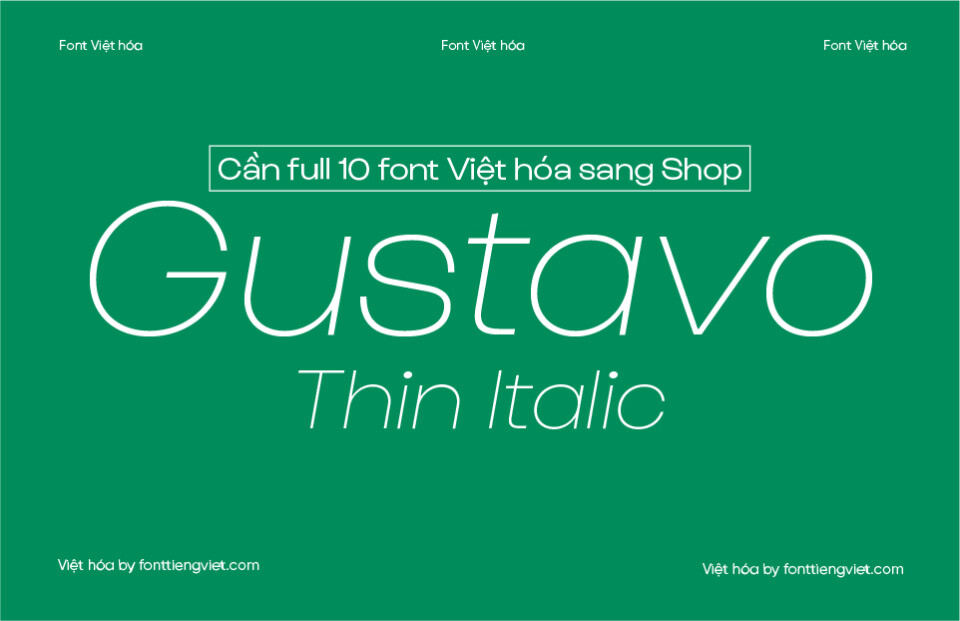
Font Việt hóa 1FTV VIP Gustavo Thin Italic
Giới thiệu về Font Việt hóa 1FTV VIP Gustavo Thin Italic
Trong thế giới đồ họa hiện đại, việc lựa chọn một bộ Font Miễn Phí chất lượng luôn là ưu tiên hàng đầu của các nhà thiết kế. Đặc biệt, mẫu Font Việt hóa 1FTV VIP Gustavo Thin Italic đang trở thành một hiện tượng nhờ vẻ đẹp thanh mảnh và sự tinh tế hiếm có. Đây là một biến thể thuộc họ phông chữ Gustavo nổi tiếng, được đội ngũ 1FTV tinh chỉnh và Việt hóa một cách công phu. Với đường nét mảnh như tơ nhưng vẫn giữ được sự sắc sảo, bộ font này mang đến một luồng gió mới cho những ai yêu thích phong cách thiết kế tối giản, sang trọng và đậm chất nghệ thuật phương Tây.
Đặc điểm nổi bật của Font Việt hóa 1FTV VIP Gustavo Thin Italic
Sự tinh tế trong từng nét chữ Italic
Điểm làm nên sự khác biệt của Font Việt hóa 1FTV VIP Gustavo Thin Italic chính là độ nghiêng hoàn hảo kết hợp cùng độ mỏng tối đa. Các ký tự được thiết kế với sự cân đối tuyệt vời, giúp văn bản trở nên thanh thoát và dễ nhìn hơn bao giờ hết. Khác với các font chữ đậm gây cảm giác nặng nề, Gustavo Thin Italic tạo ra không gian thở cho bản thiết kế, giúp người xem tập trung vào nội dung một cách tự nhiên. Từng dấu câu và ký tự tiếng Việt được đặt đúng vị trí, đảm bảo không bị lỗi font khi sử dụng trên các phần mềm đồ họa chuyên nghiệp.
Tính ứng dụng đa dạng trong thực tế
Dù có vẻ ngoài mảnh mai, nhưng Font Việt hóa 1FTV VIP Gustavo Thin Italic lại cực kỳ linh hoạt trong nhiều bối cảnh khác nhau. Bạn có thể sử dụng nó cho các tiêu đề tạp chí thời trang, thiệp mời đám cưới sang trọng, hoặc các trích dẫn ý nghĩa trên mạng xã hội. Đối với học sinh và sinh viên, đây là lựa chọn tuyệt vời để làm nổi bật các ý tưởng trong bài thuyết trình hoặc thiết kế bìa báo cáo sáng tạo. Sự thanh lịch của nó giúp nâng tầm giá trị hình ảnh, biến những nội dung đơn giản trở nên có hồn và chuyên nghiệp hơn rất nhiều.
Tại sao nên chọn Font Việt hóa 1FTV VIP Gustavo Thin Italic cho dự án của bạn?
Khả năng tương thích hoàn hảo
Tối ưu hóa trải nghiệm người dùng
Việc sử dụng một bộ font đã được Việt hóa kỹ lưỡng như Gustavo Thin Italic giúp tiết kiệm thời gian đáng kể cho người dùng. Thay vì phải tự chỉnh sửa dấu hay tìm kiếm các bộ font thay thế, bạn có thể bắt tay ngay vào việc sáng tạo. Font chữ này không chỉ đẹp về mặt thị giác mà còn đảm bảo tính dễ đọc, một yếu tố then chốt trong truyền thông và giáo dục. Nó giúp thông điệp của bạn được truyền tải một cách nhẹ nhàng nhưng vẫn đầy ấn tượng.
Kết luận về bộ font chữ cao cấp